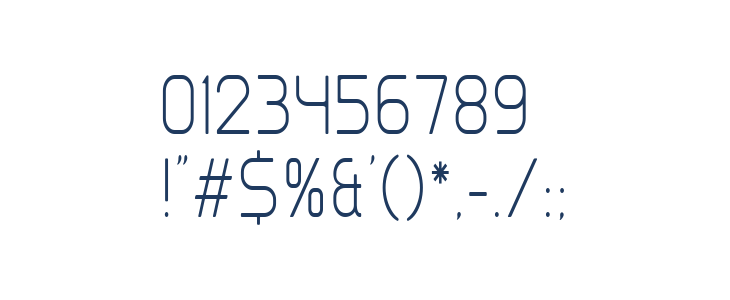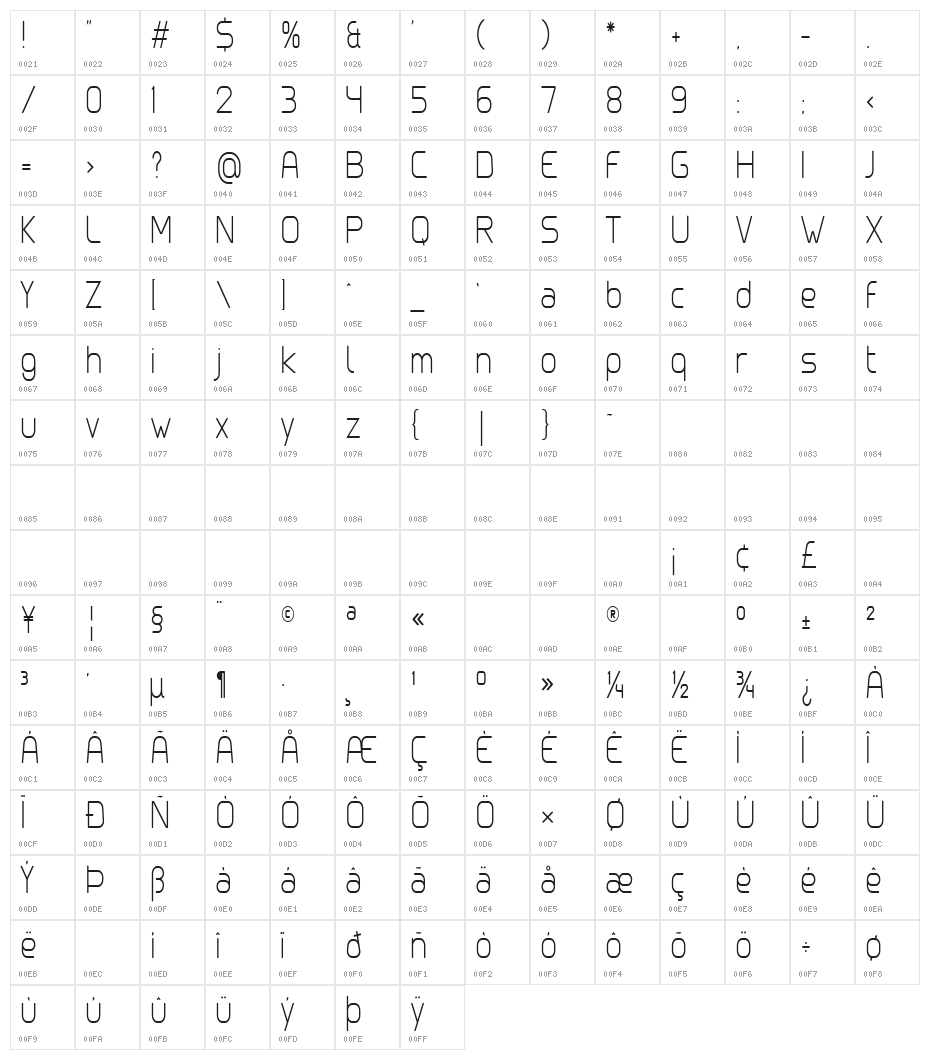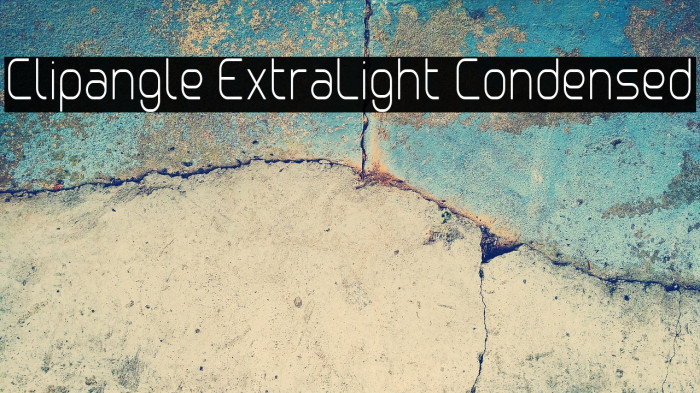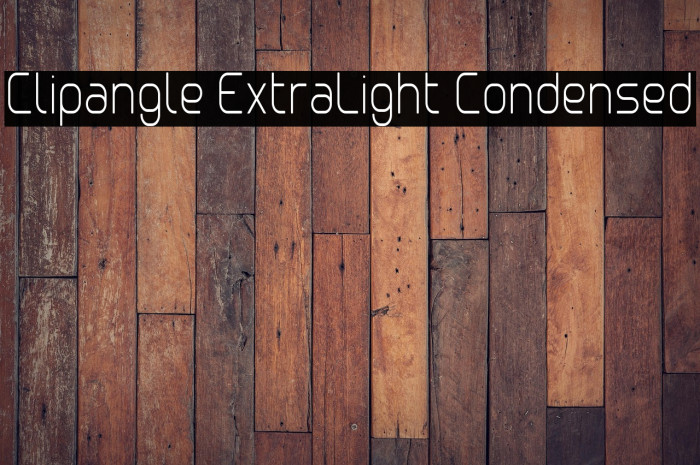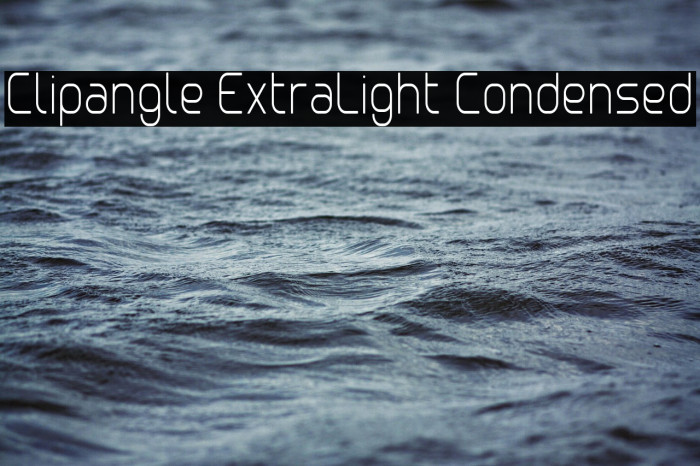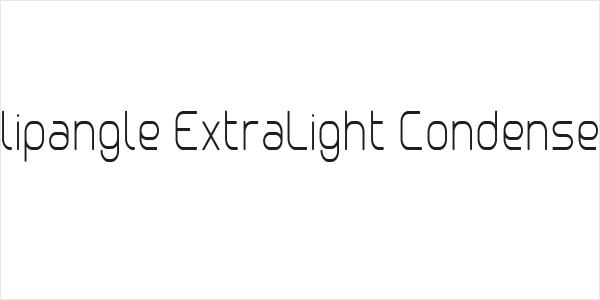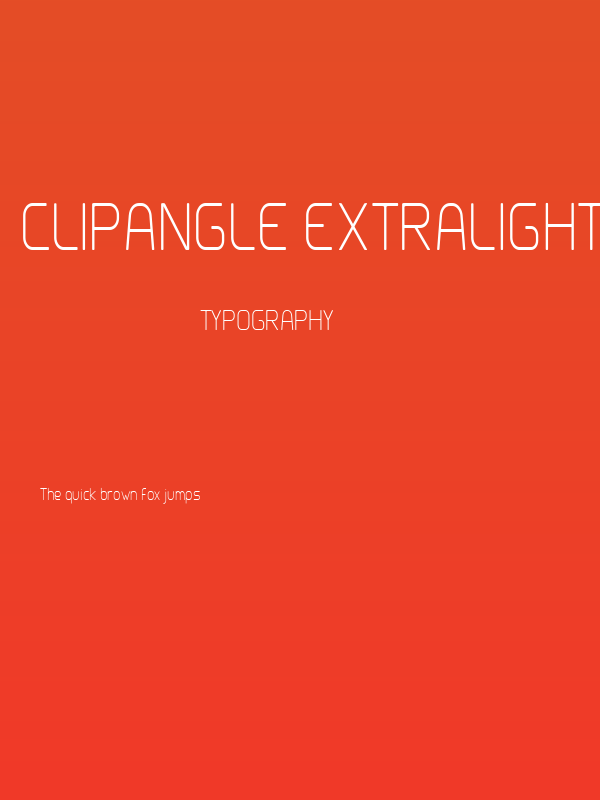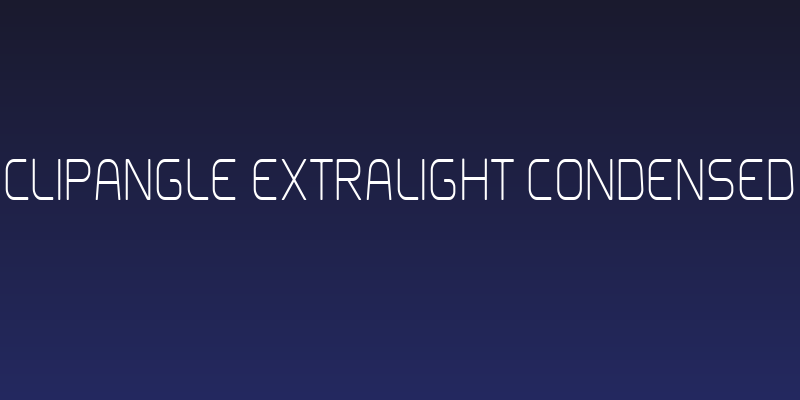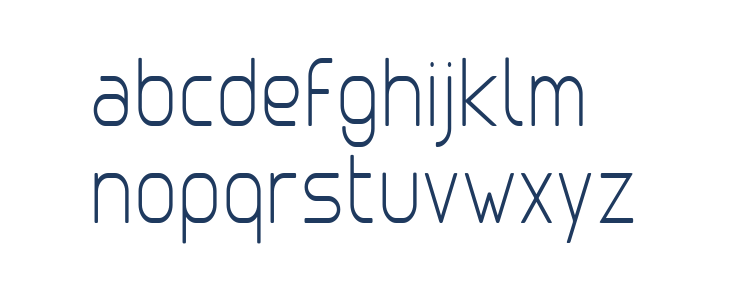
Clipangle ExtraLight Condensed Font
| Anwendungsfall | Headlines, Body text, Logos |
| Vorgeschlagene Projekte | Ideal for branding, editorial design, and digital interfaces where a modern and clean aesthetic is desired. |